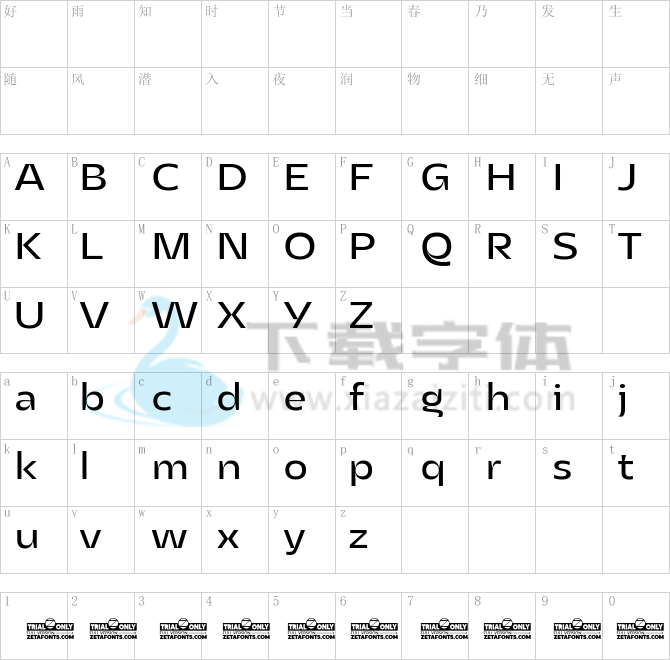
Asgard Trial Fit.ttf字体下载,这款字体结构工整、笔画清晰,兼顾美观与易读性,适用于标题、正文、海报、包装、LOGO 等多种场景。字形优雅稳定,风格百搭耐看,适配日常排版与创意设计,让文字呈现更舒适、更具质感。Asgard Trial Fit.ttf字体下载一笔一画,皆是细节,以均衡的比例、流畅的线条打造舒适视觉体验,字形端正大气,风格简约现代。无论是商业设计、品牌宣传还是日常排版,都能轻松驾驭,让文字更有格调与力量。Asgard Trial Fit.ttf字体下载字体下载。
• 字体名称:Asgard Trial Fit